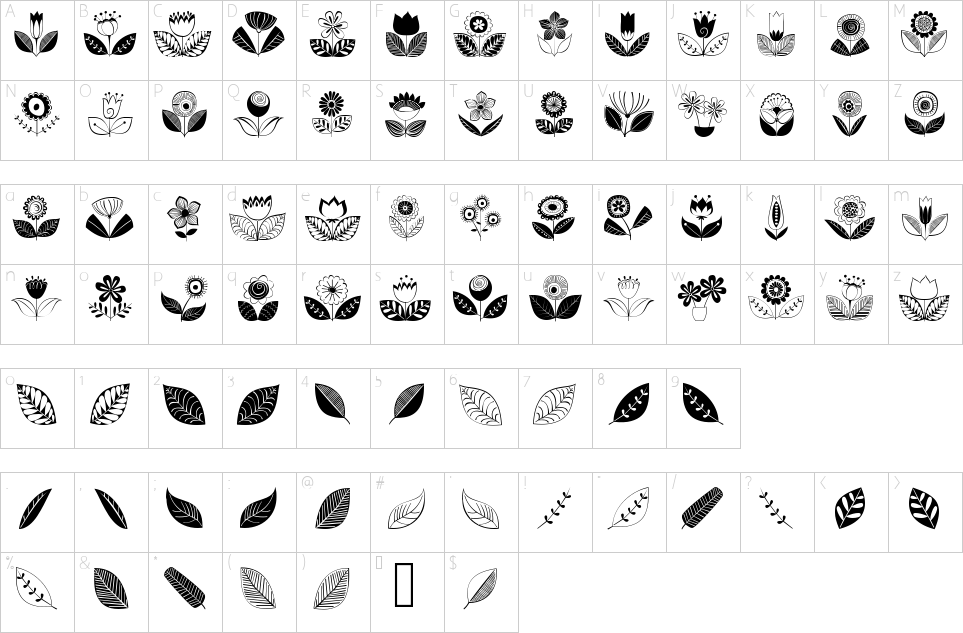
Doodle Dings 2 Retro Flowers Font – Download Grátis
A Doodle Dings 2 Retro Flowers é uma fonte criada pela designer Emily Spadoni, disponível para download tanto no sistema Windows quanto Mac. Esta fonte retrata elementos florais e desenhos artesanais de um modo que remete à estética retro e vintage, tornando-a ideal para quem busca adicionar um toque especial a designs de layout web ou impressão em papel. Com sua design minimalista e colorido, ela é perfeita para criar texturas diferentes e variadas, adequada tanto para nomes bonitos quanto para headlines chamativas. Com uma download total de 23.462 vezes, os criadores provaram o sucesso desta fonte gráfica. A Doodle Dings 2 Retro Flowers oferece aos designers a liberdade de experimentar elementos retro e desenho artesanal em seus projetos sem sair da categoria do gráfico gratuitamente.